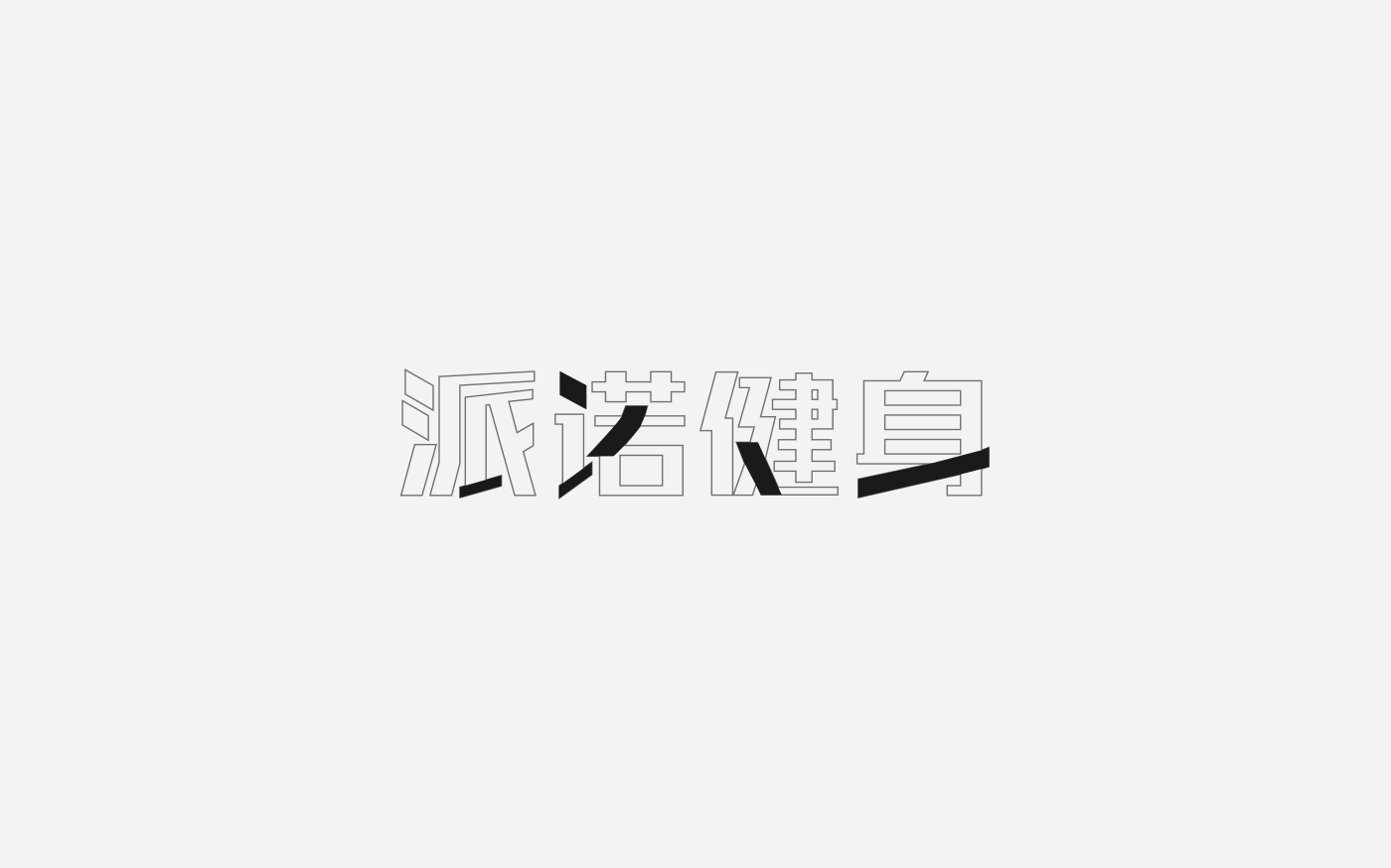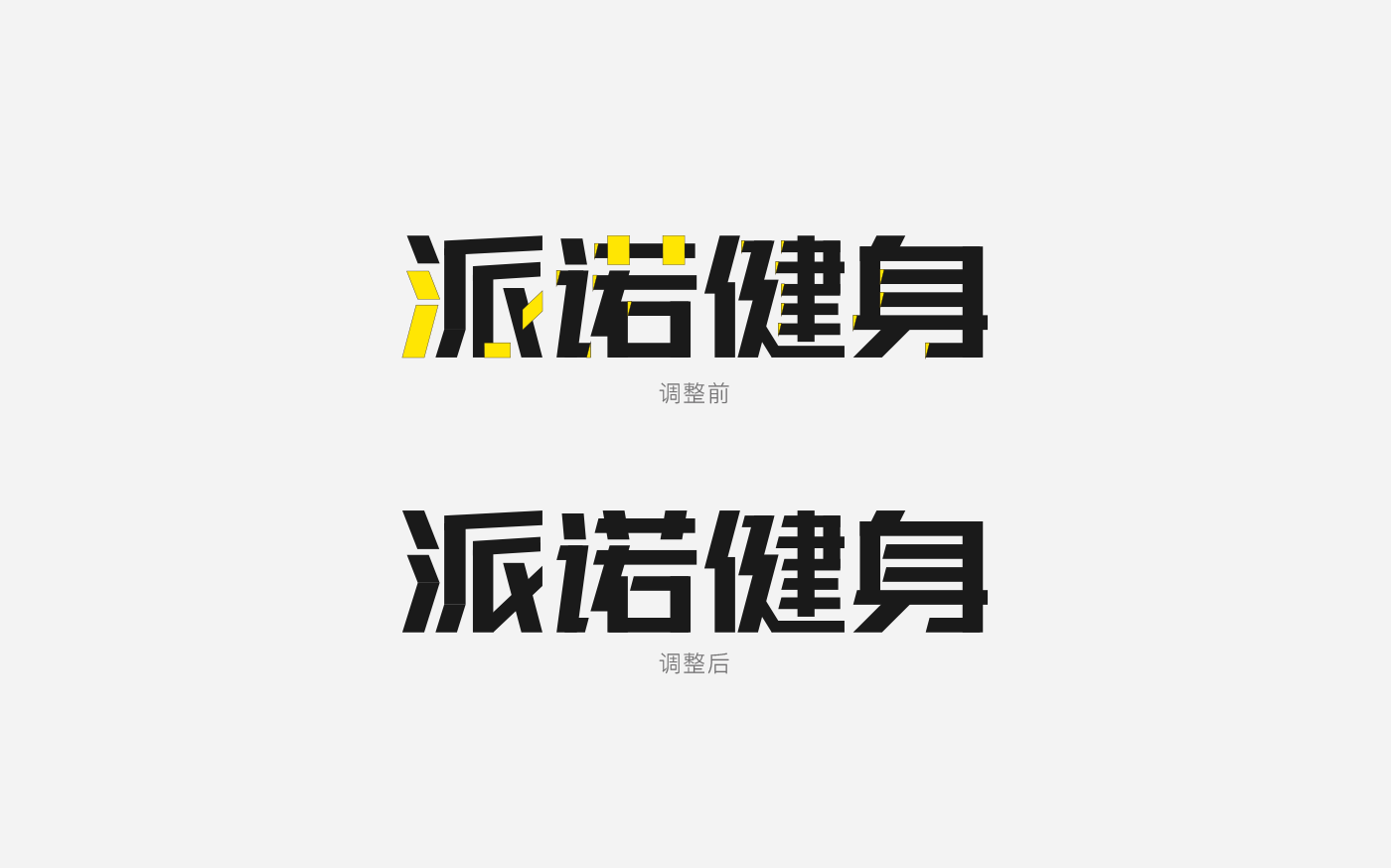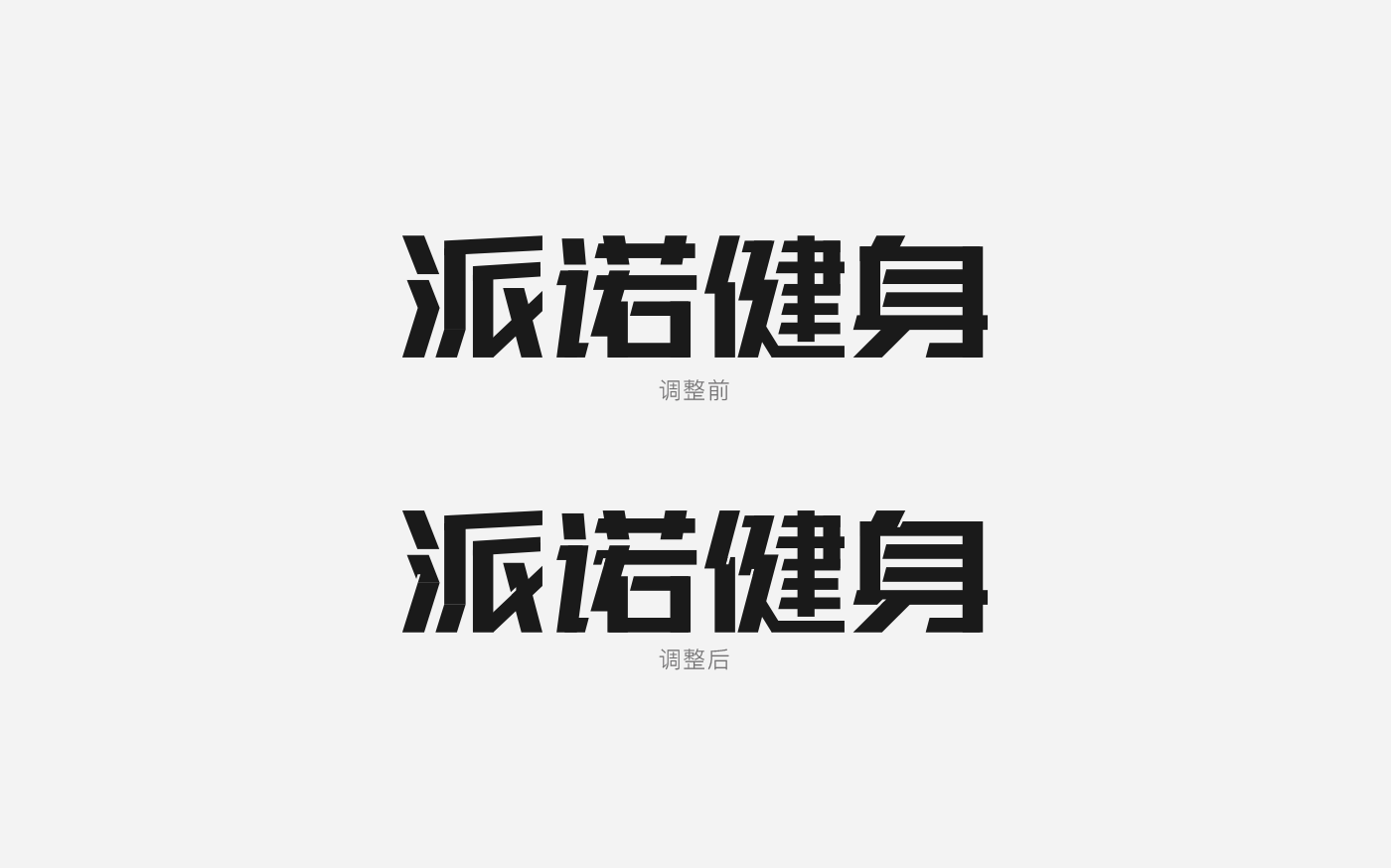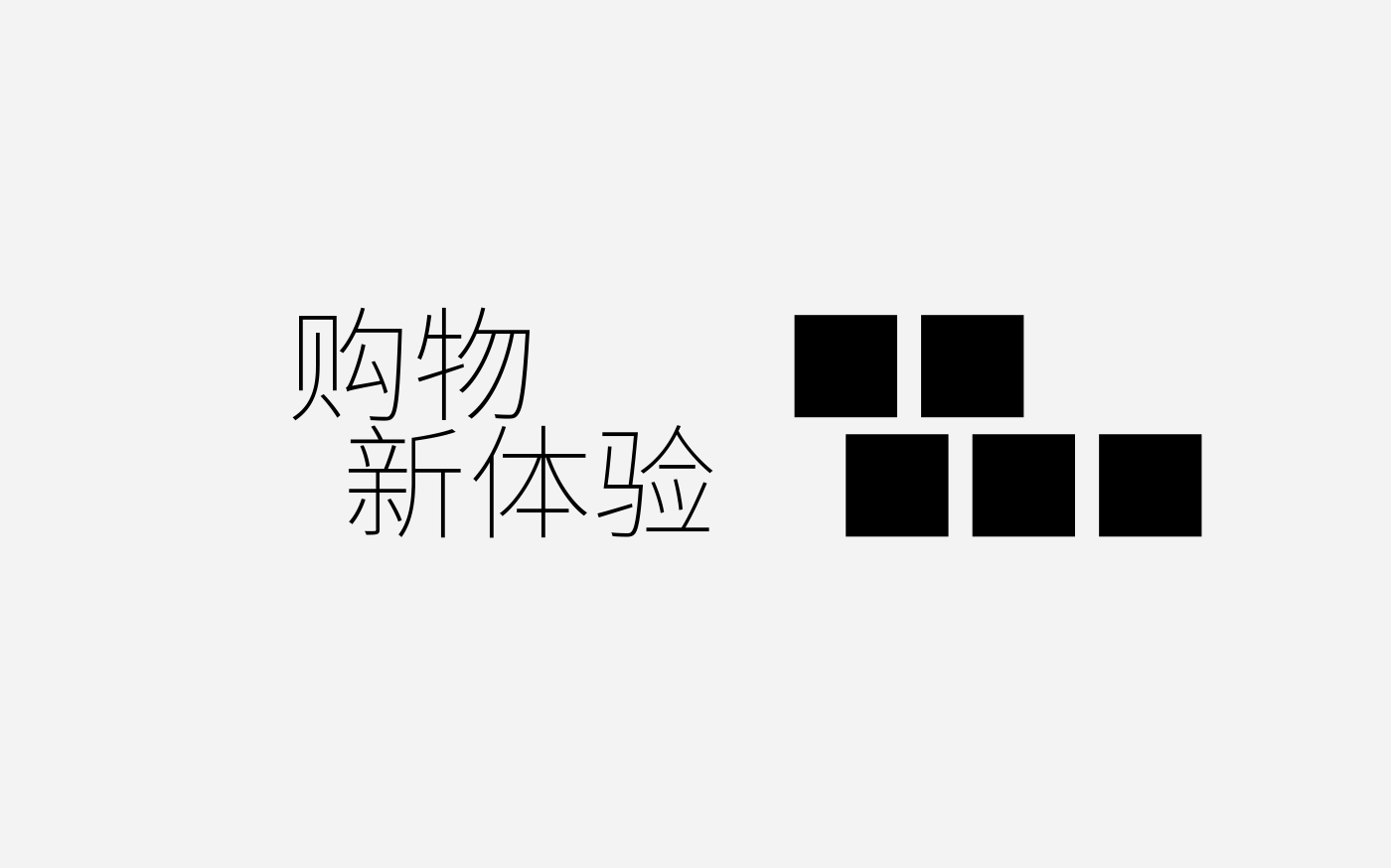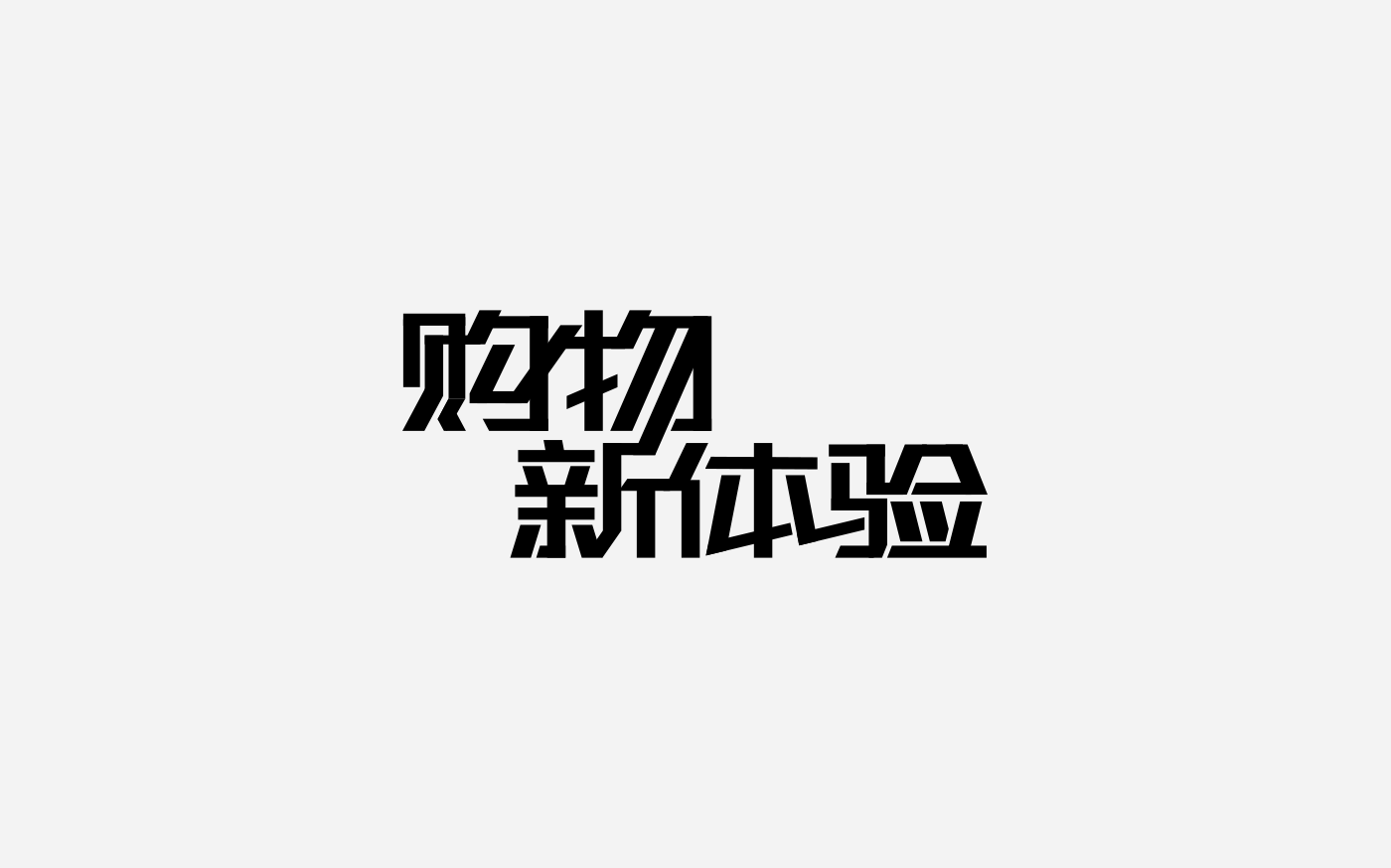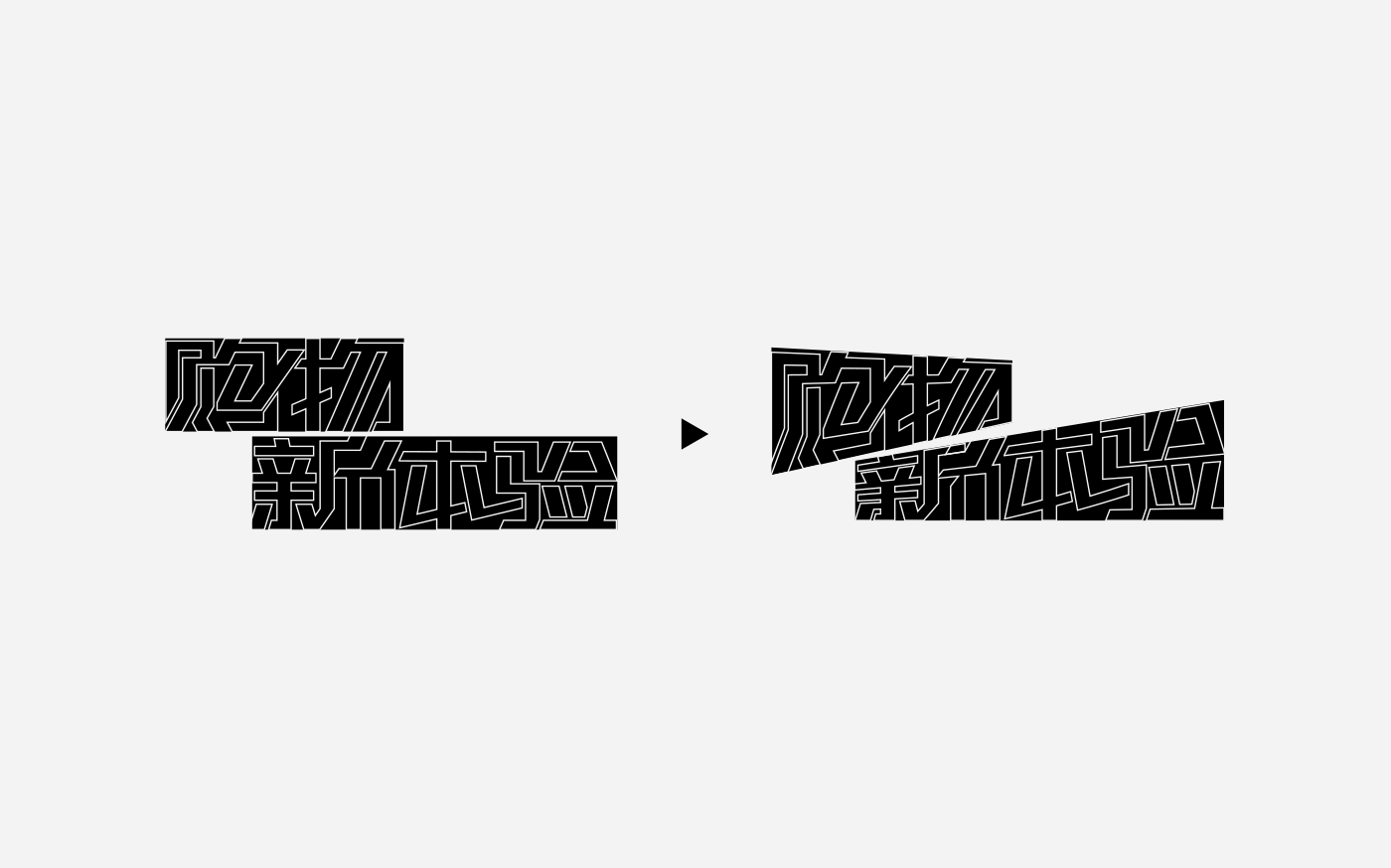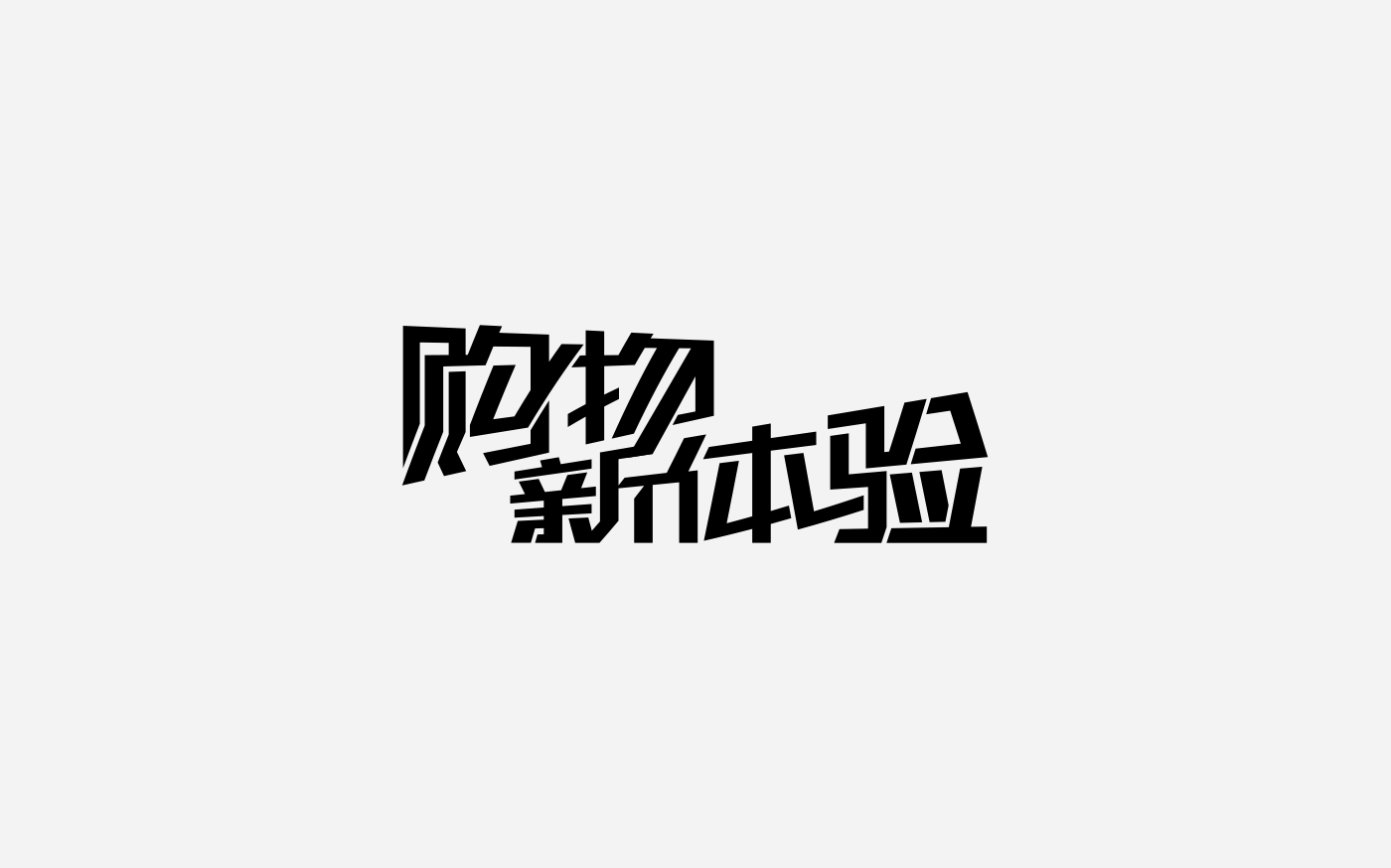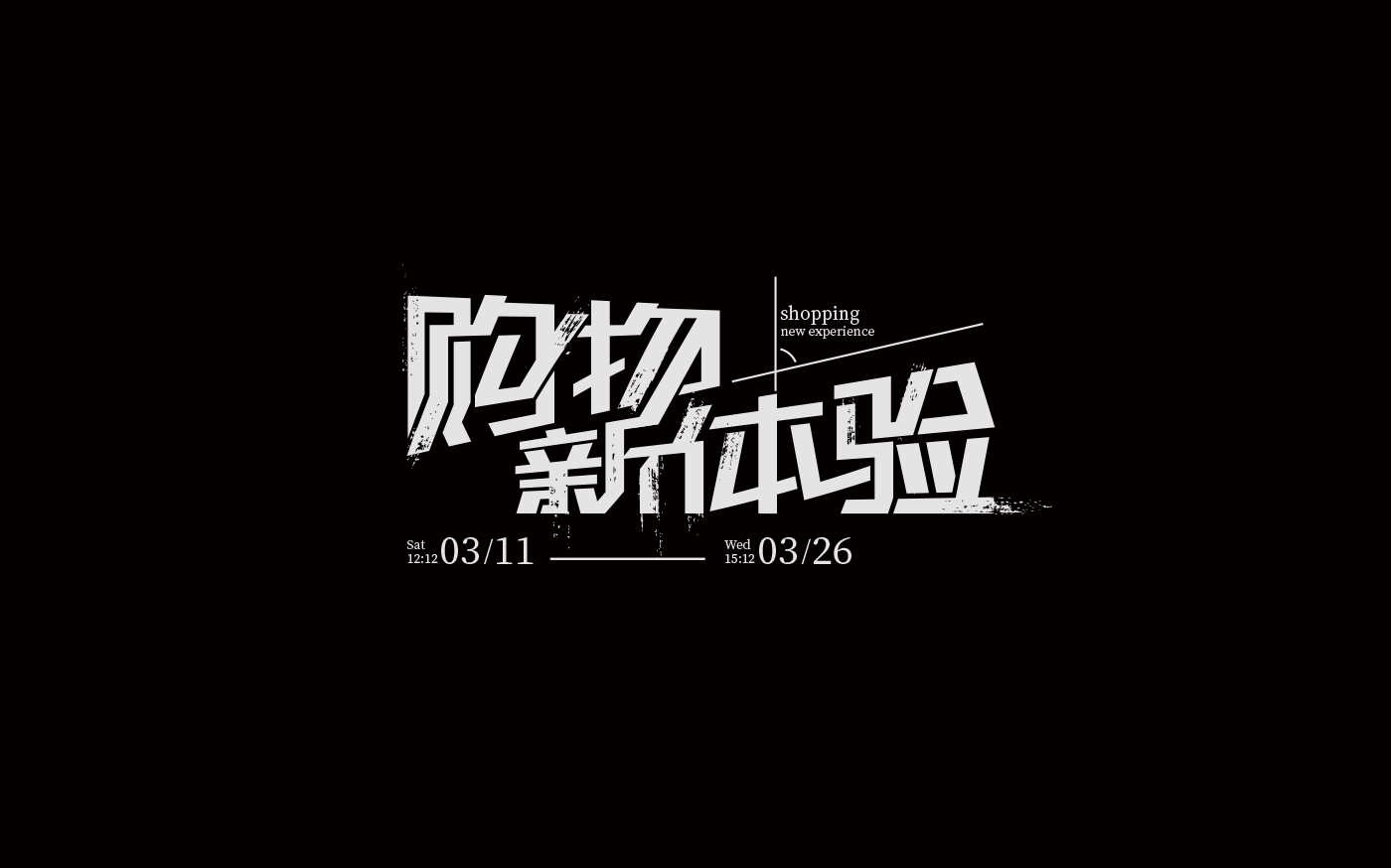
经验 | 矩形字体设计案例讲解
矩形字体设计,多为字体方正或硬朗而名,也可以理解为用矩形去设计字体;因为这类字体方便快捷容易出效果,在海报中的标题字和企业标准字中都可以看到矩形字体的身影。
上面这些案例就是矩形风格的字体设计了,在设计中,粗细变化与几何形体的灵活运用,都能为为字体添加了些许年代感与设计感。
本篇用两个简单的字体案例来带你感受下矩形字体设计的便捷。
健身类字体使用矩形的方式去设计是较为合适的,因为粗壮的矩形给人一种力量感与稳重感。新手在做之前可以使用字库字挑选出合适的字体作为形式参考,一个对的参考是绝对的加分项,避免设计调性出现偏差。
参考分析
第一种和第二种字体呈现的方式都是横细竖粗的形式,但第一种字体比较高挑,整体力量感较弱;第二种成方块形,给人感觉更为稳重与有富有力量感。
设计分析
在设计前可以简单对字体进行分析,黑色区域笔画有往上提和部分是有弧度的,我们可以将这部分进行简化或统一角度去进行设计。然后将笔画与角度进行调整,设计出字体基本型来进行对比并与参考字体进行明显区分。
添加细节
根据前期分析重新构造基本字形后,相对比原字字体,新构造的字形比原先更简洁。但对比起来还是和字库字体没什么区分,字体中缺少了细节与独特感。可以考虑给字体做连笔处理或者添加笔触细节等去提升设计的形式感。
为营造出字体的设计细节,在这将“派”字笔划进行了连笔设计;其他字体的笔划末端则进行了切角处理,使其和其他笔划进行视觉统一;“诺”字草字头竖笔向内倾斜,和前面进行了呼应。
处理细节的方式有很多,例如上面在原字体上给字体笔划之间加入刻痕效果,让字体细节更为丰富。
我们看一下最后呈现的效果:
“购物新体验”这个字体属性偏向于标题类,所以我们在设计的时候需要考虑这类字体的整体氛围。
根据字体的内容,在这将字体分成了两行,整体呈阶梯状,也可以用其他形式去体现。
草稿绘制
排列完后可以用画笔工具在字体的基础上大概画一下草稿,将字体做连接处理增加整体的设计感;连笔时可以选择邻近和角度相近的笔画进行连接,这样能避免字体识别性降低。
将画好的草稿用矩形绘制出来后发现笔画连接处不够流畅协调,这时可以将笔画连接相交处进行断开处理(尽量保持断开处位置与角度的统一)。
深入刻画
将连笔交界处进行断开后,字体整体显得更为流畅协调。但这整体氛围仍不够强烈,可以将字体深入处理,例如将字体变换角度、添加字体效果、添加字体纹理和添加字体版式的设计感等处理手法都可以体现整体的氛围感。
在这可以先将字体的角度进行更改看看效果。
在Illustrator中可以选择透视扭曲对字体进行变换角度,和photoshop的自由变换是一个原理。变换角度并没有一个特定的数值,根据调整后的舒适度去进行变换即可。
将字体成梯形交错排列,整体视觉冲击力和氛围更强,字体更显张力。
最后将字体进行版式深化,在这也在字体中添加了一些纹理去营造字体的氛围感,当然也可以添加字体效果和进行颜色搭配,让字体更好的的呈现更美的效果。